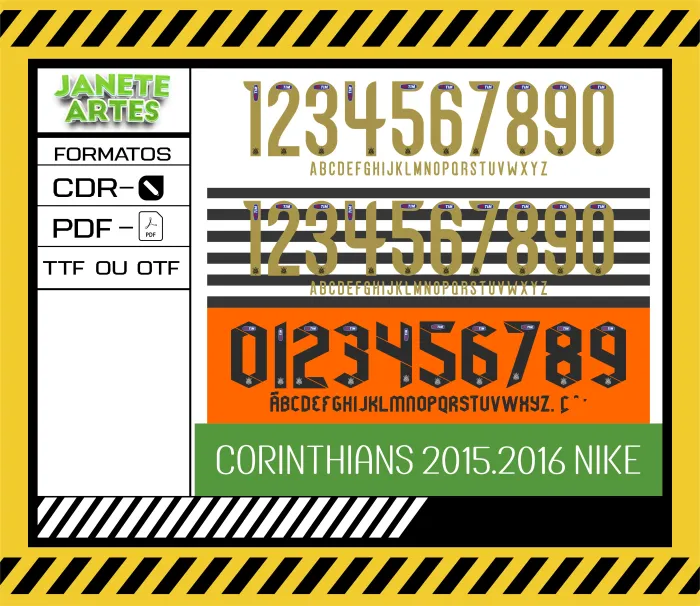
Fonte de Time Tipografia Corinthians 2015 - 2016
A história por trás do estilo Corinthians 2015 - 2016
Imagine a emoção de um torcedor vibrando a cada lance, vestido com uma camiseta que traz o verdadeiro estilo da equipe do seu coração. Em 2015 e 2016, o Corinthians marcou uma época com uma tipografia única e cheia de personalidade, que hoje é reconhecida por fãs do Brasil inteiro. Com a Arte Fonte Corinthians 2015 2016 para Camiseta, você pode levar essa paixão para o dia a dia, criando camisas que parecem saídas diretamente das arquibancadas! 🎉
- Tipografia fiel à usada pelo Corinthians nas temporadas de 2015 e 2016, perfeita para personalizar camisas, blusas e camisetas.
Bom saber que esse arquivo pode ser usado tanto para camisetas básicas para eventos, quanto para presentes personalizados para amigos corinthianos. Inclua o nome do seu grupo ou sua frase favorita ao lado da fonte e tenha uma peça exclusiva! ⚽
- Qual o diferencial do produto? A fidelidade ao estilo do Corinthians 2015 - 2016 para quem ama o time.
Com a Arte Fonte Corinthians 2015 2016 para Camiseta, sua paixão pelo Corinthians ganha um novo jeito de ser mostrada, fácil e rápida de aplicar na sua peça favorita.